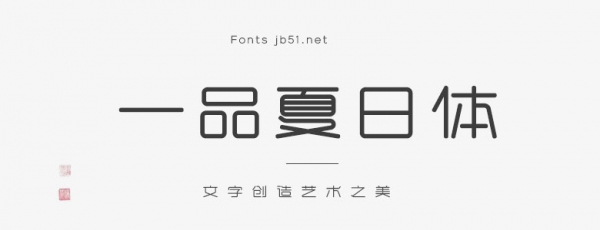
一品夏日體的筆畫設(shè)計(jì)一氣呵成、簡約時(shí)尚,字體末端采用切角設(shè)計(jì),柔化了筆形的同時(shí),與飽滿整齊的字形特征相輔相成,視覺上不僅表達(dá)了清涼的概念,也傳遞了圓形、廓形的舒適感與親和力。
在線體的處理上,設(shè)計(jì)師將字體結(jié)構(gòu)的圓與豎的對稱性自然結(jié)合,達(dá)到視覺上的和諧,更具有設(shè)計(jì)性。
“一品夏日體”除了擁有中文字樣外,還設(shè)計(jì)了英文以及數(shù)字字樣。圓潤的線條使字體更加風(fēng)趣,筆畫連接處的倒角設(shè)計(jì),看起來俏皮、跳躍、充滿青春活力,宛如夏日荷塘里蹦蹦跳跳的蛙。